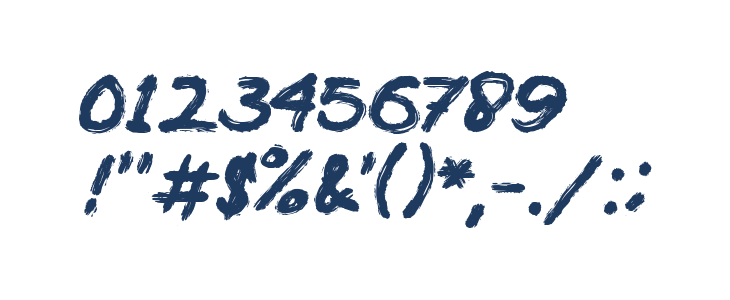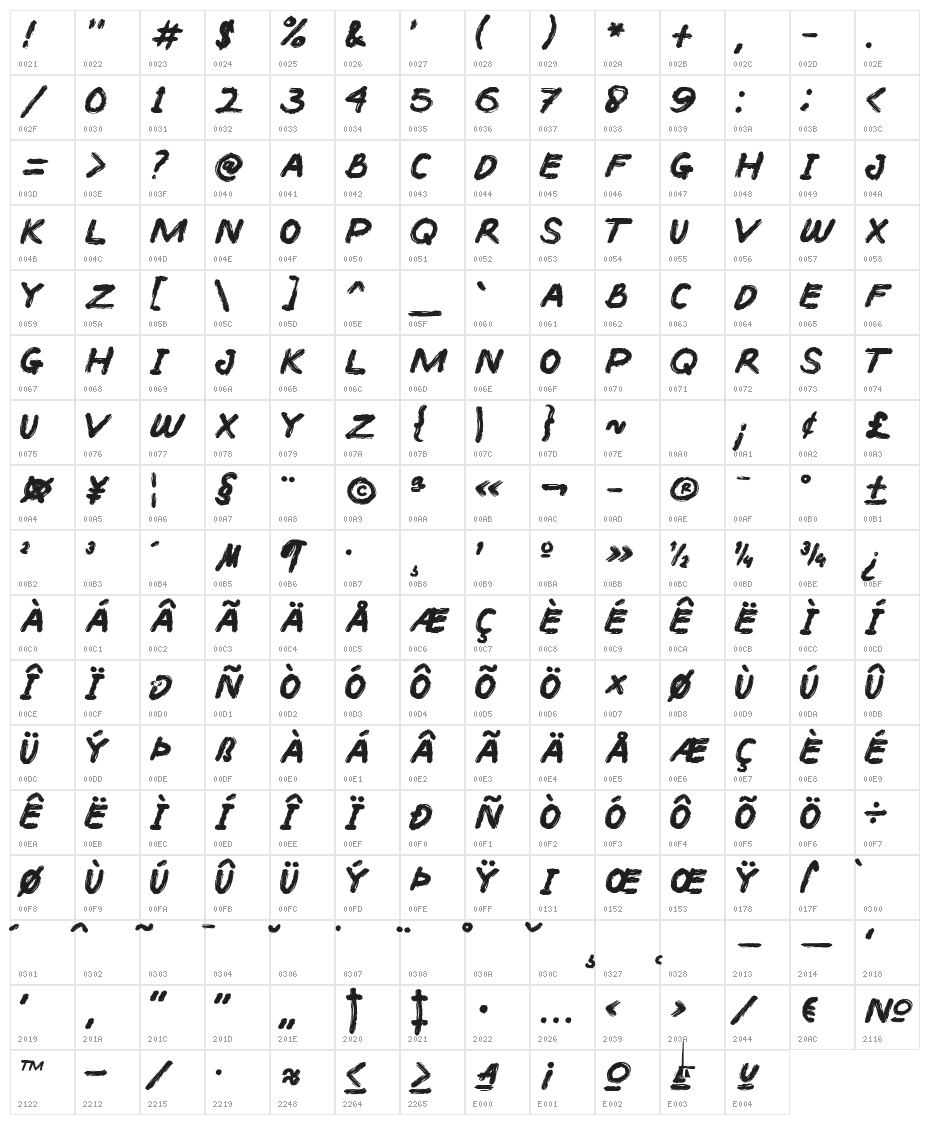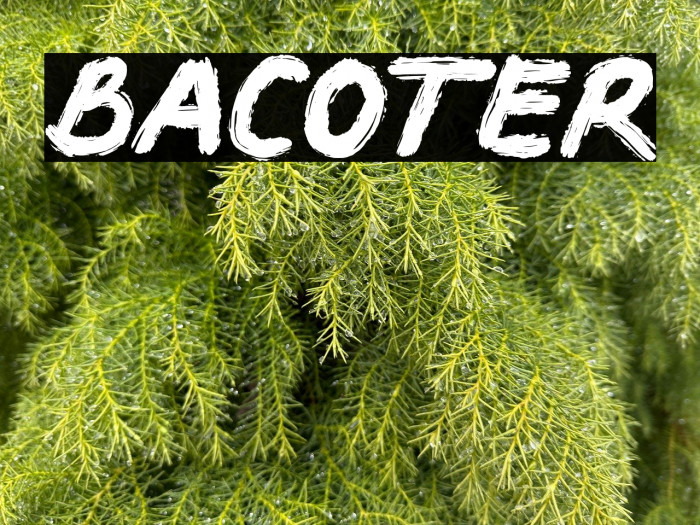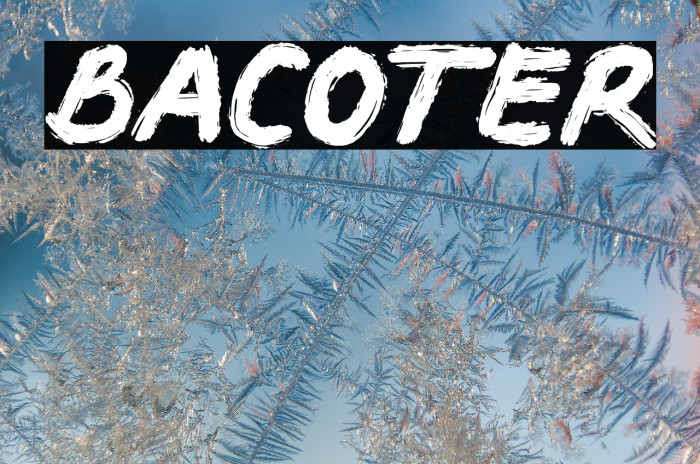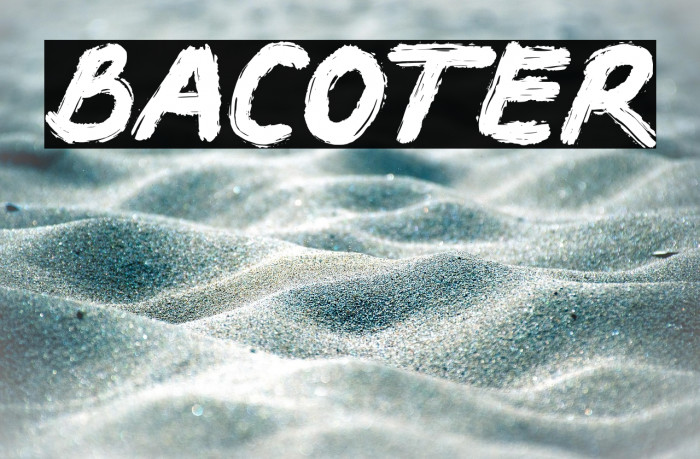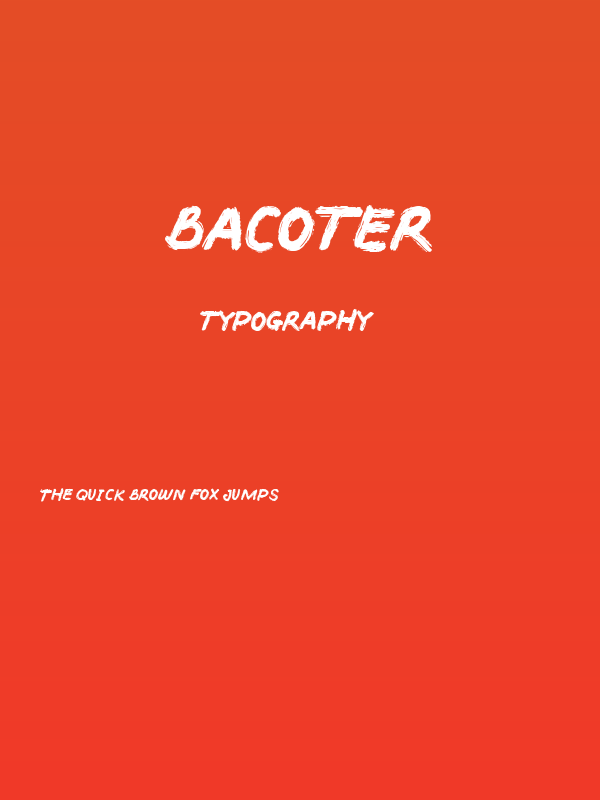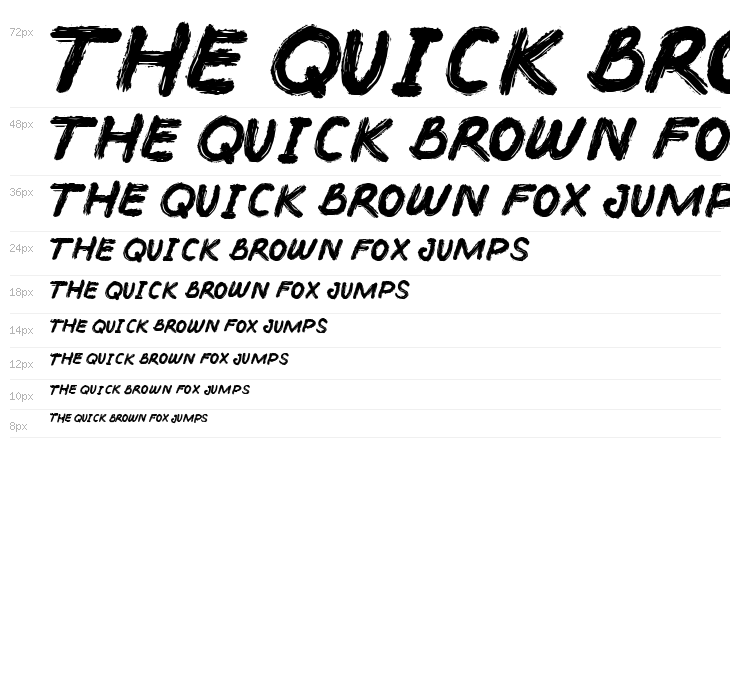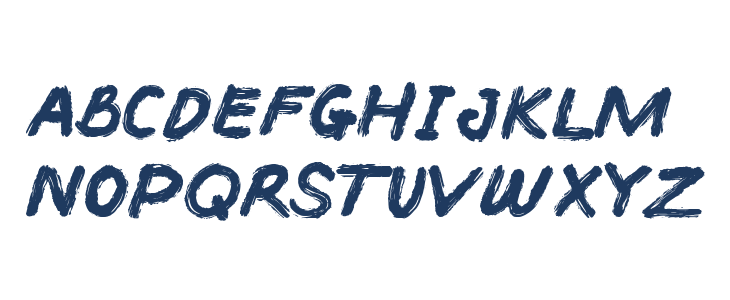
BACOTER Font
| Stile generale | Modern, Artistic |
| Progetti proposti | Ideal for projects that require a creative and artistic touch, such as posters, album covers, branding for artistic ventures, or any design that seeks to convey energy and movement. |